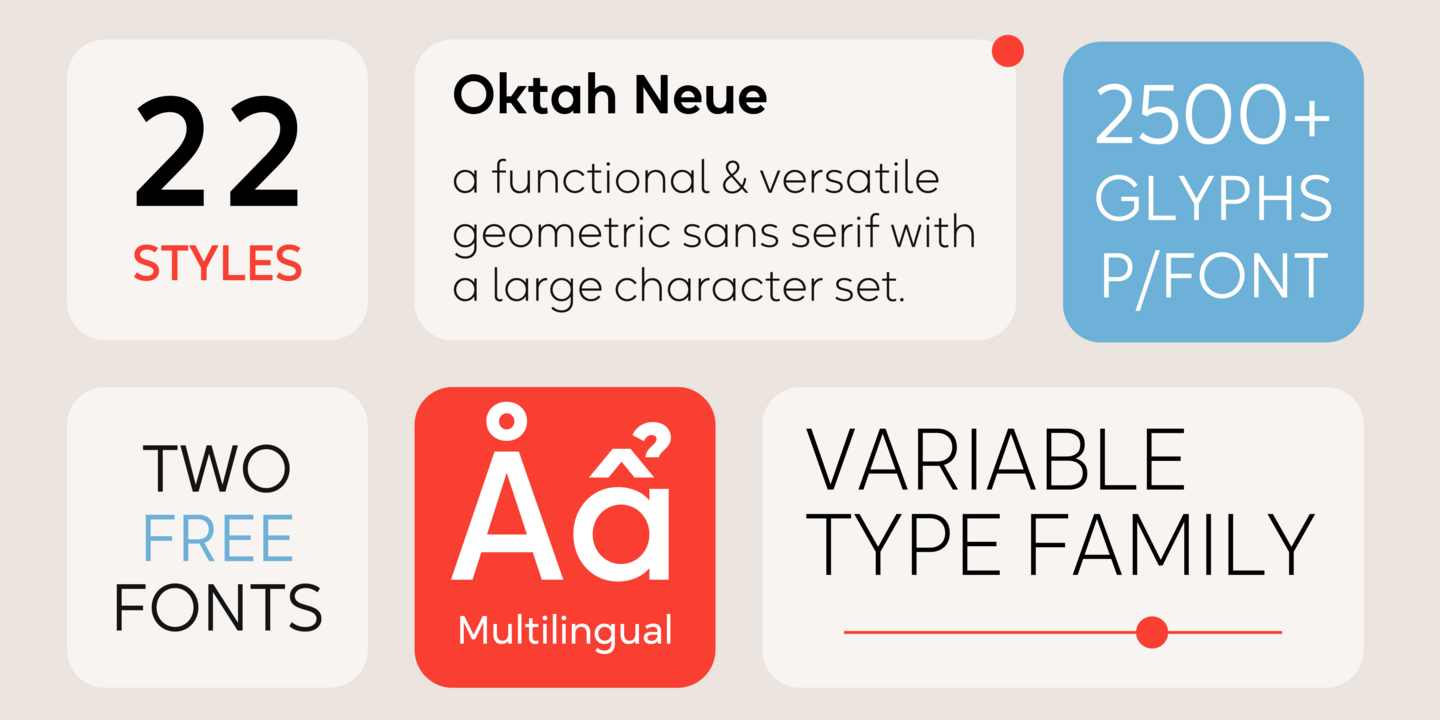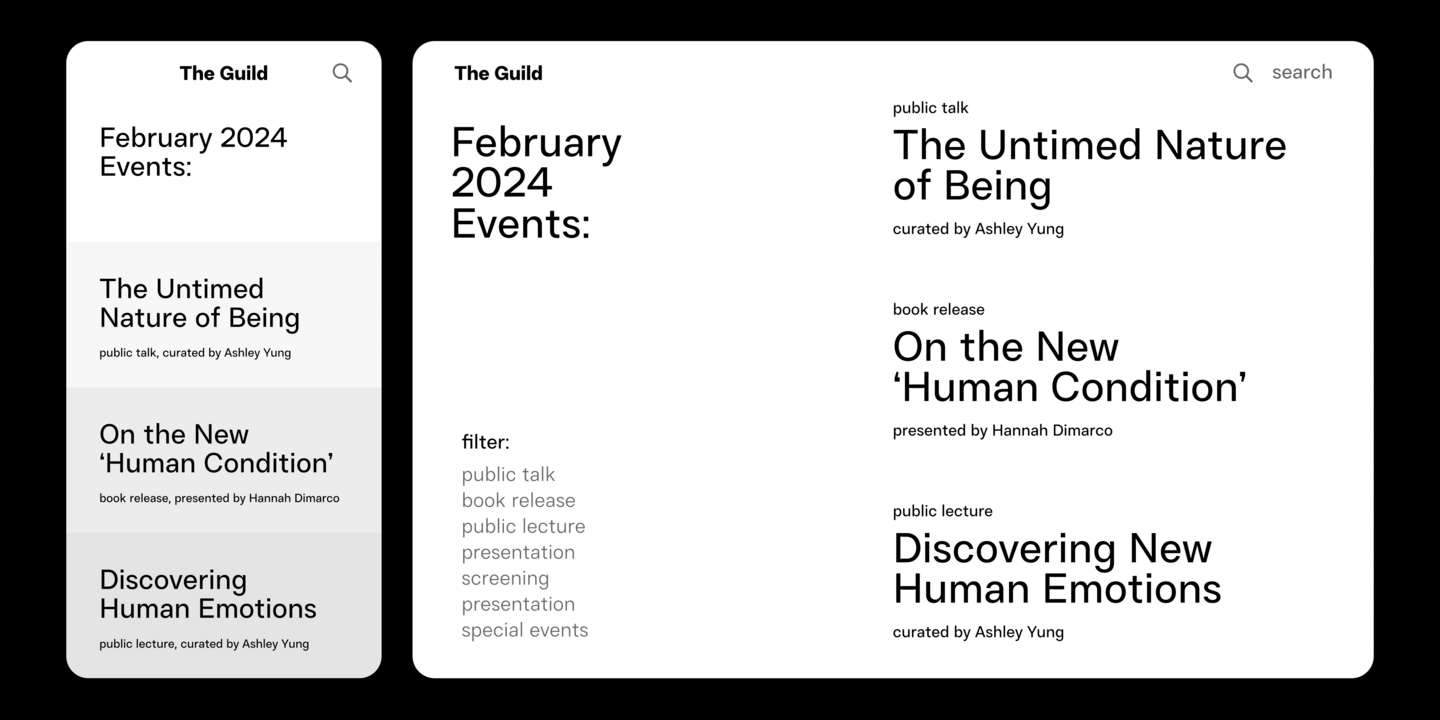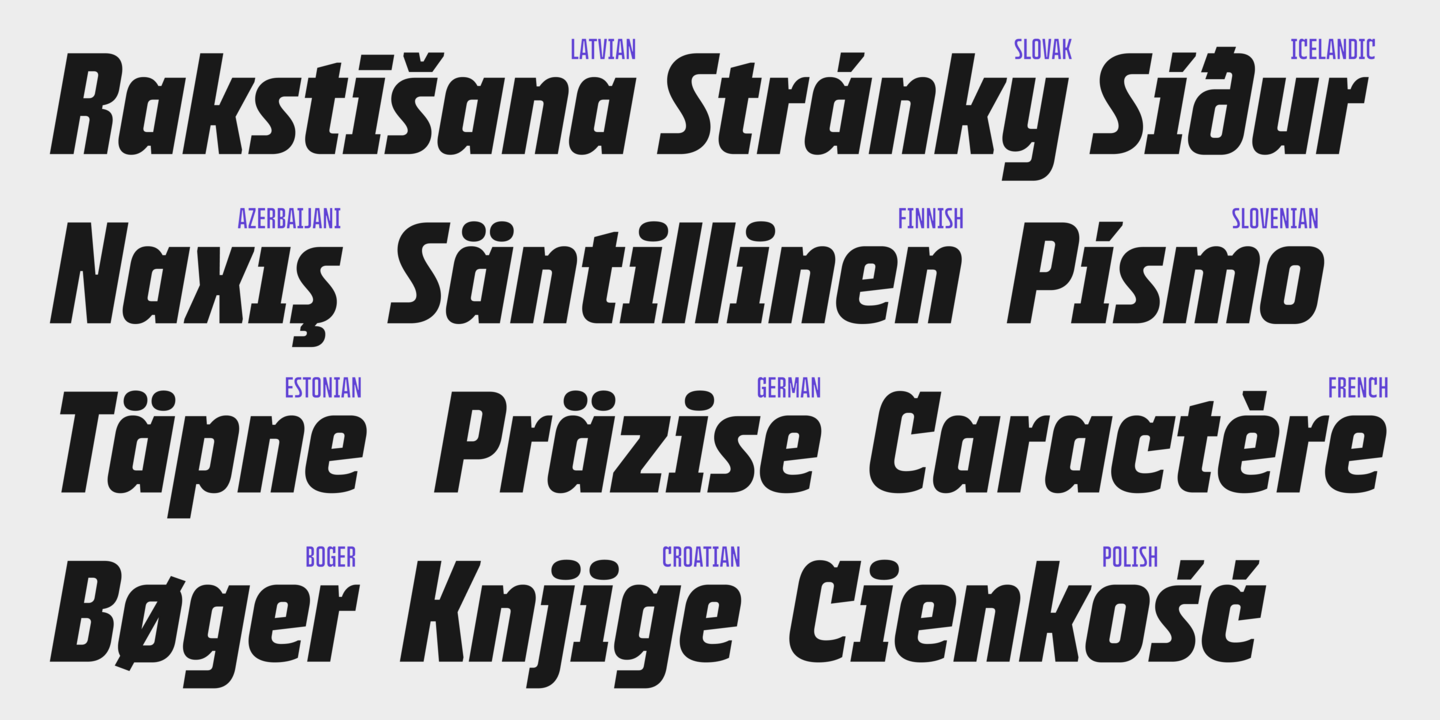
Polices Groteskly Yours
Groteskly Yours Studio (GYS) est un studio familial fondé par Eugene et Anna. Le studio se consacre à l'élaboration de solutions typographiques innovantes et à la fourniture d'outils exceptionnels pour les créatifs dans divers secteurs et domaines. La philosophie de conception de GYS repose sur le principe que les caractères doivent être polyvalents, fiables et faciles à utiliser.
Resist Sans est une famille de caractères sans empattement à l'esprit libre qui harmonise le désir inné de rébellion avec une tendance à l'uniformité. D'aspect neutre et minimaliste, Resist Sans s'adapte facilement à un large éventail de besoins en matière de conception. Resist Sans se décline en deux sous-familles (Text et Display), offrant un total de 28 styles et plus de 900 caractères dans chaque police.
Oktah Neue est une famille de caractères géométriques sans empattement qui se décline en 22 styles. Les principales caractéristiques d'Oktah Neue sont une excellente lisibilité, des formes de lettres géométriques simples et un faible contraste dans tous les styles. Oktah Neue est incroyablement polyvalent, ce qui en fait un excellent choix pour divers scénarios tels que la conception de sites Web, les applications mobiles, la conception éditoriale et l'image de marque.
Greisen est une famille de caractères sans empattement fonctionnelle qui se décline en 18 styles. Caractérisé par des proportions condensées, des caractères lisibles et une apparence robuste, le Greisen s'adapte facilement à une variété de projets de conception - de la conception de sites Web à la conception éditoriale, en passant par l'emballage et l'image de marque. Greisen transmet un sentiment de sécurité et de fiabilité, ce qui en fait un excellent choix pour les projets nécessitant une esthétique solide et digne de confiance.
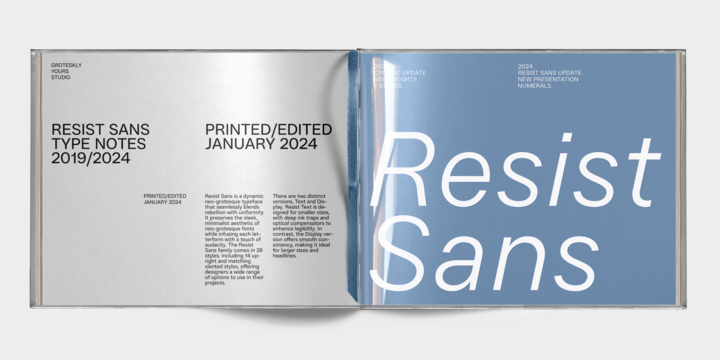
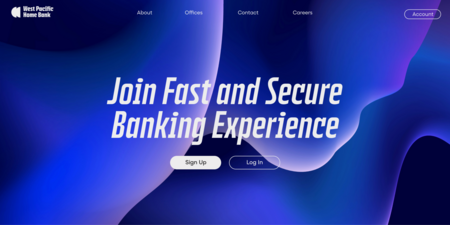
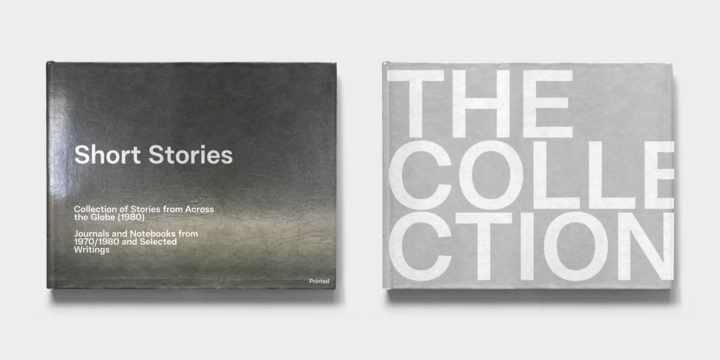
Grotesquement vôtre
Les caractères GYS sont un équilibre entre créativité et fonctionnalité. Privilégiant toujours une approche de la conception centrée sur l'utilisateur, Eugène et Anna développent des polices de caractères qui combinent un design innovant, une qualité élevée et des caractéristiques conviviales.
Fondateur et directeur de projet
Eugène Tantsurin
Eugene est un créateur de caractères autodidacte et le fondateur de Groteskly Yours Studio. Après avoir obtenu son diplôme à l'Université de Bangkok en 2018, il a commencé à travailler sur des projets de conception personnels et a finalement développé un intérêt pour la conception de caractères. Chez GYS, Eugene gère les projets de détail et personnalisés et maintient la communication avec les clients
Cofondateur et directeur de la création
Anna Remm
Anna a toujours été passionnée par les caractères typographiques et tout ce qui s'y rapporte. Elle a obtenu un diplôme en design graphique en 2016 et a passé plusieurs années à travailler comme graphiste. Avec Eugene, elle a cofondé GYS en 2019. En tant que directrice créative, Anna supervise et guide les aspects créatifs du processus de création de caractères.